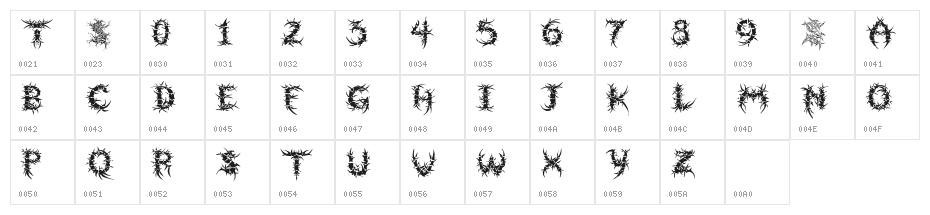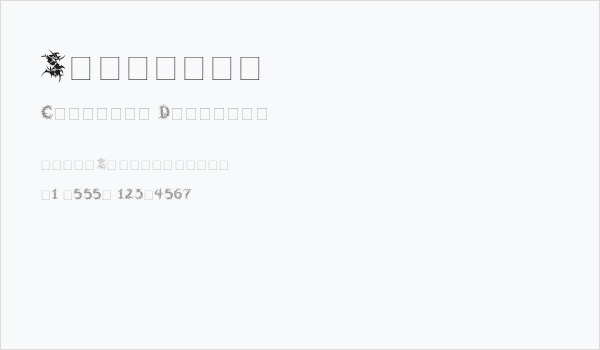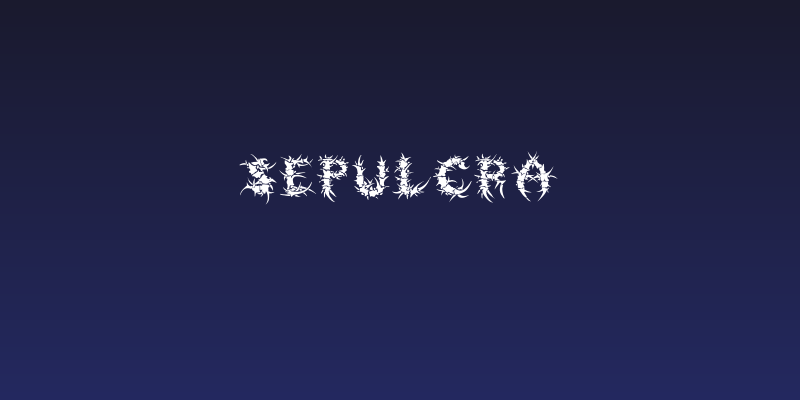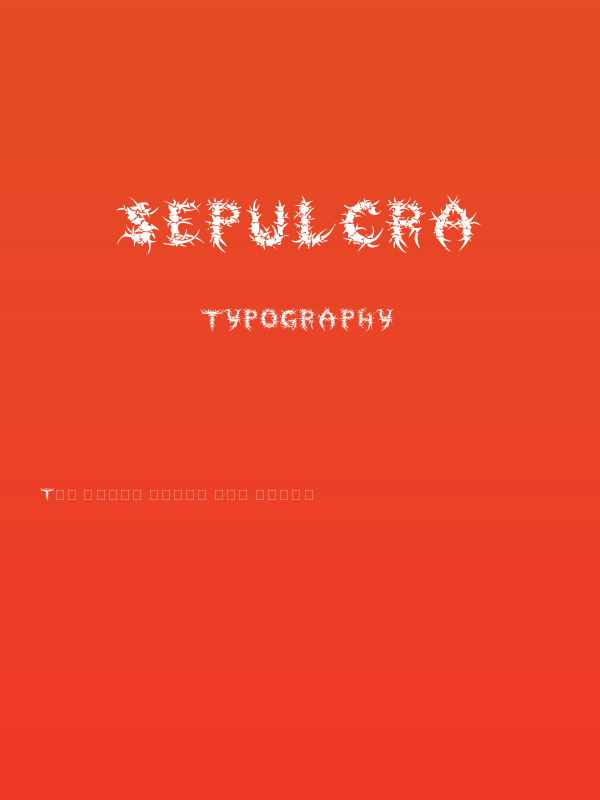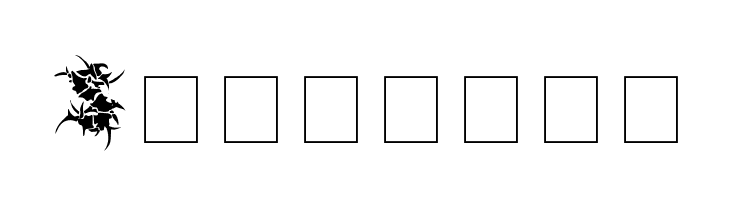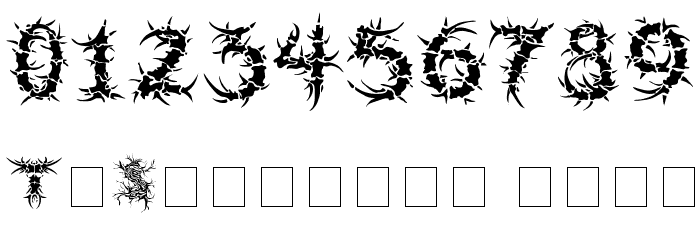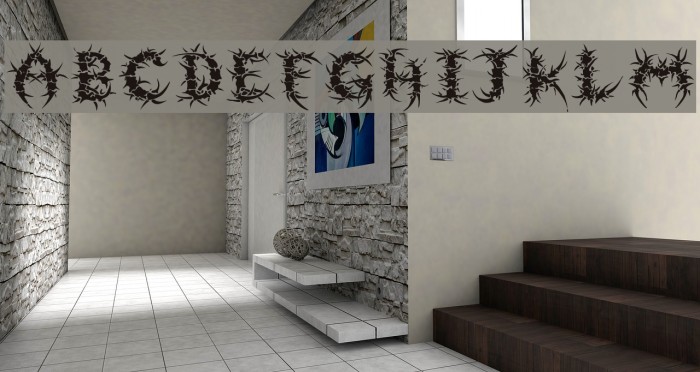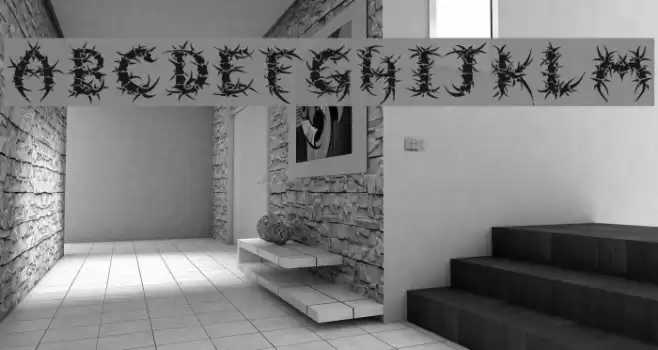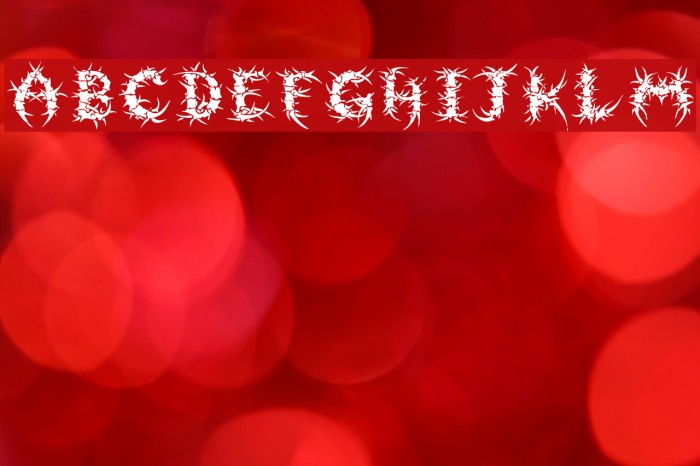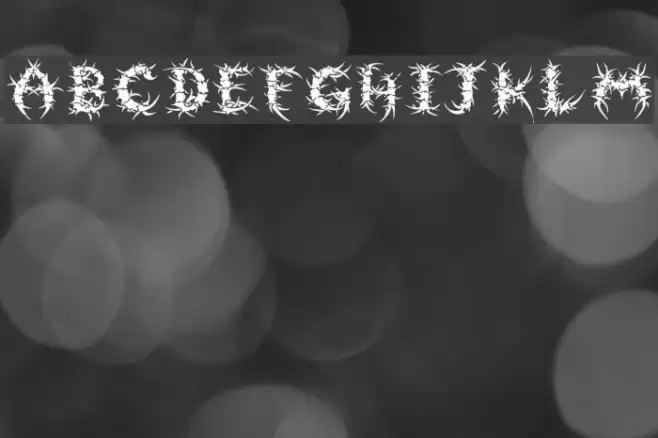
Sepulcra Font
✎ Gothic
| Stile generale | Gothic, Decorative |
| Progetti proposti | Ideal for horror-themed posters, album covers, gothic event invitations, and any project requiring a dramatic and intense visual impact. |